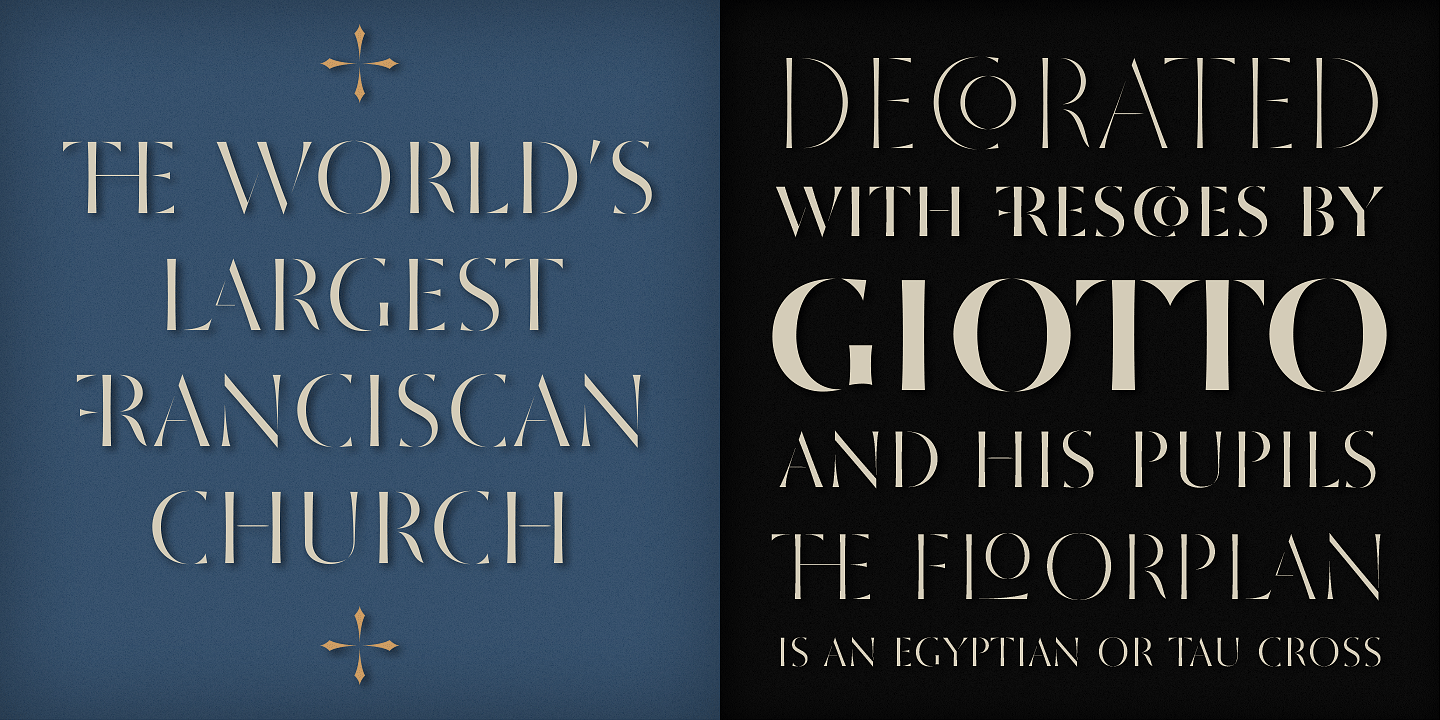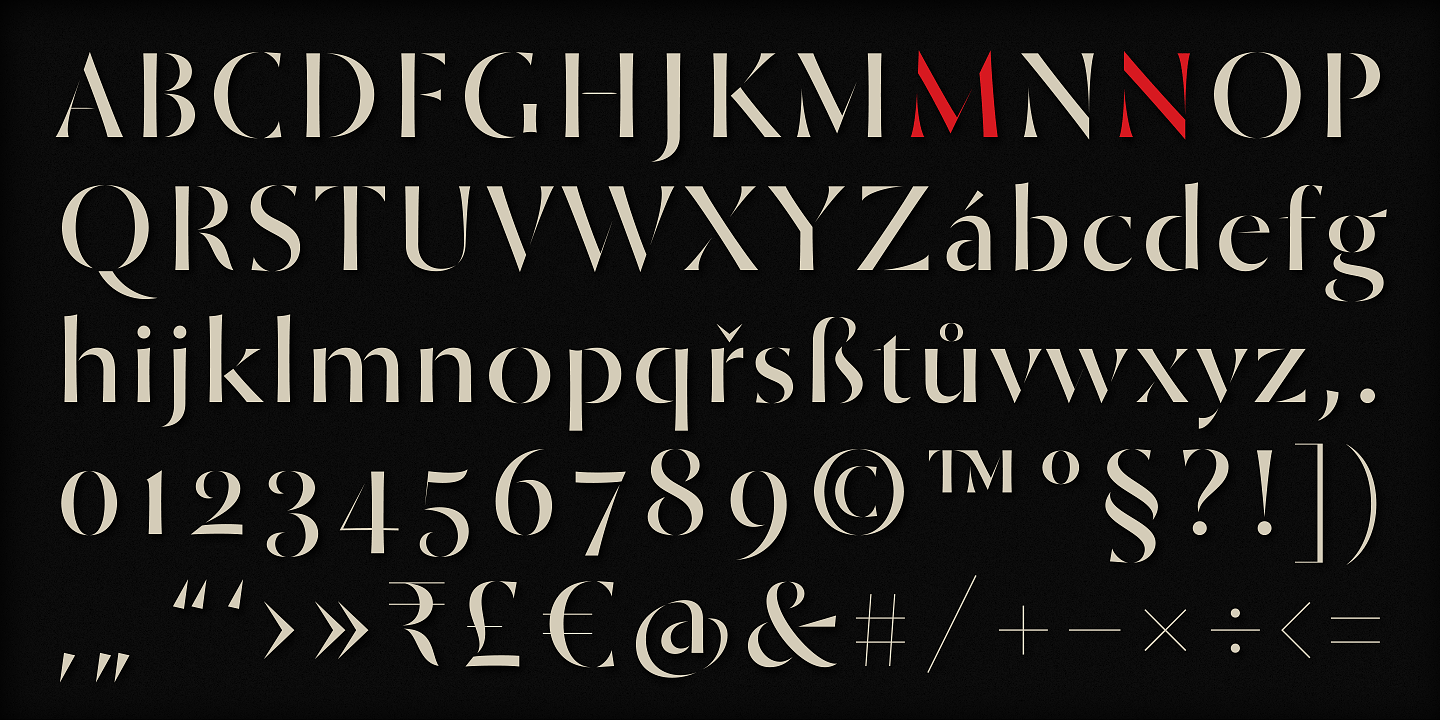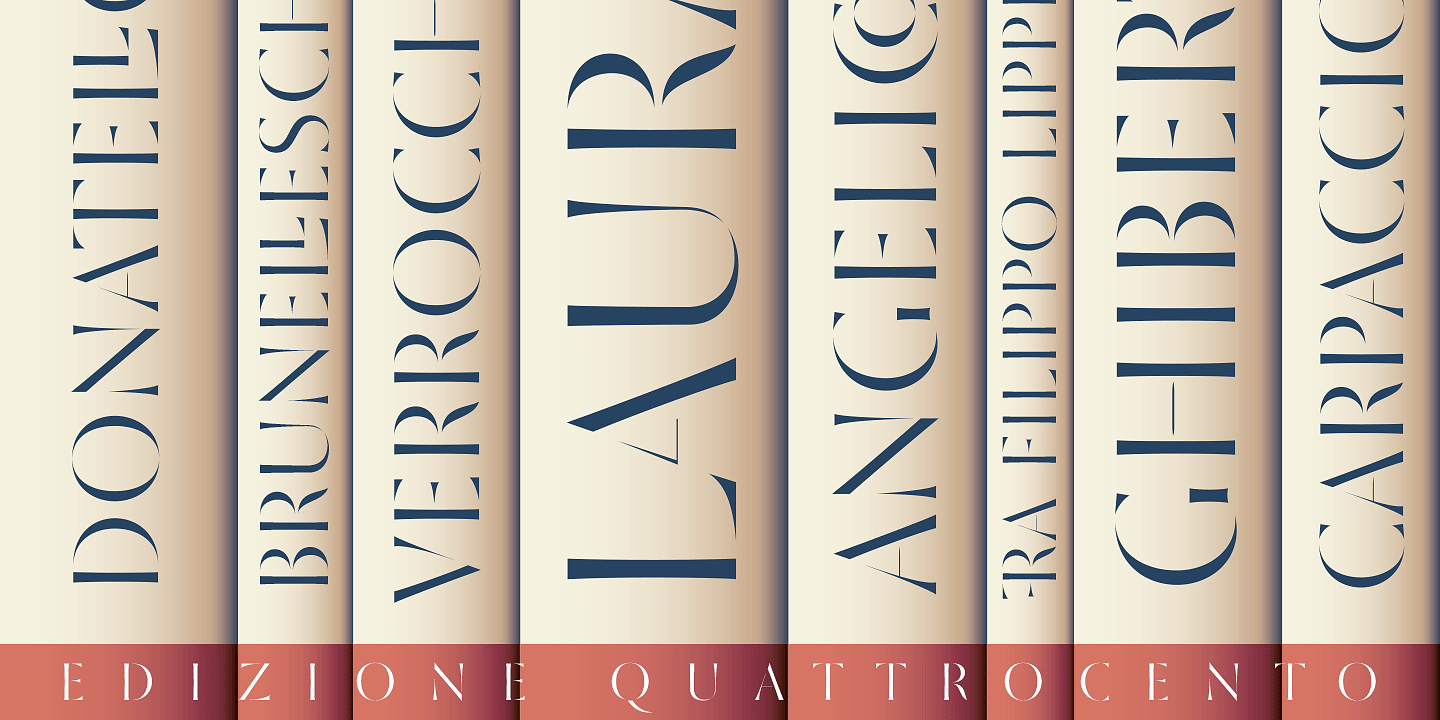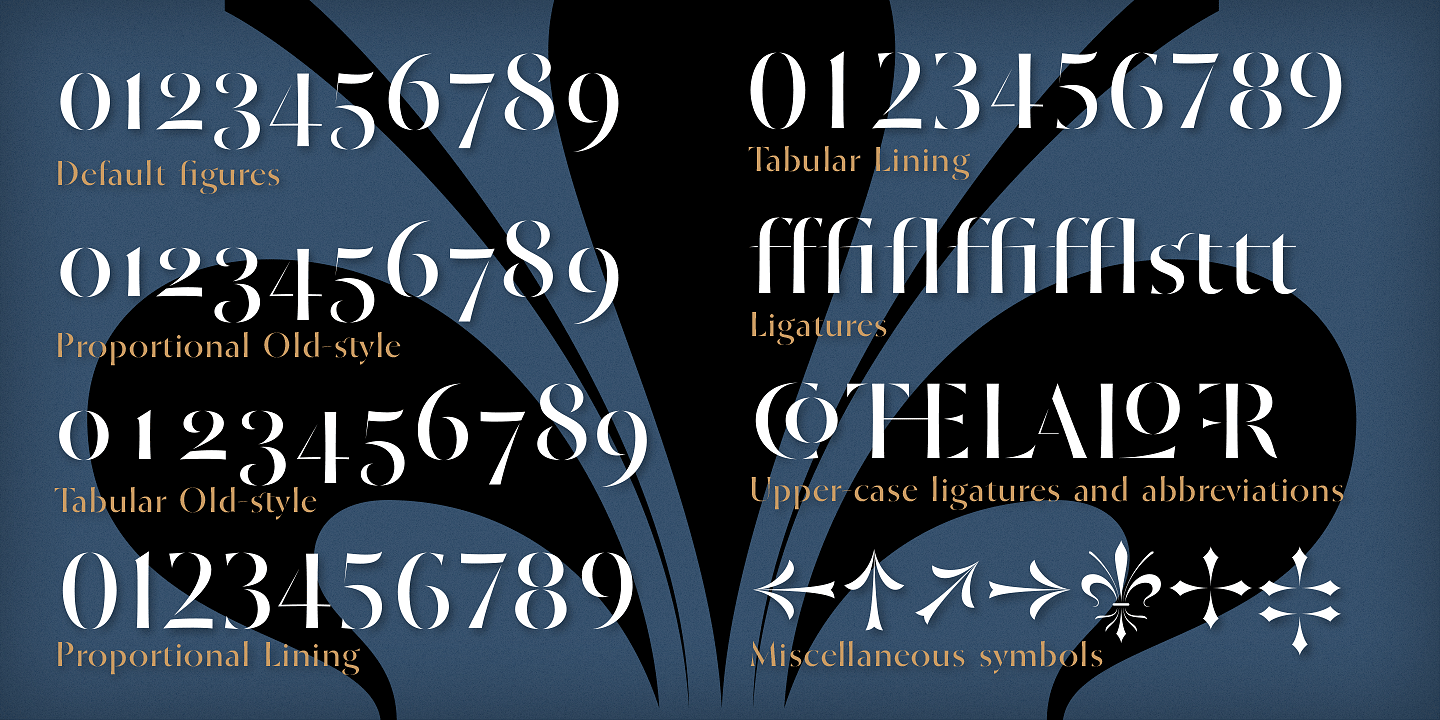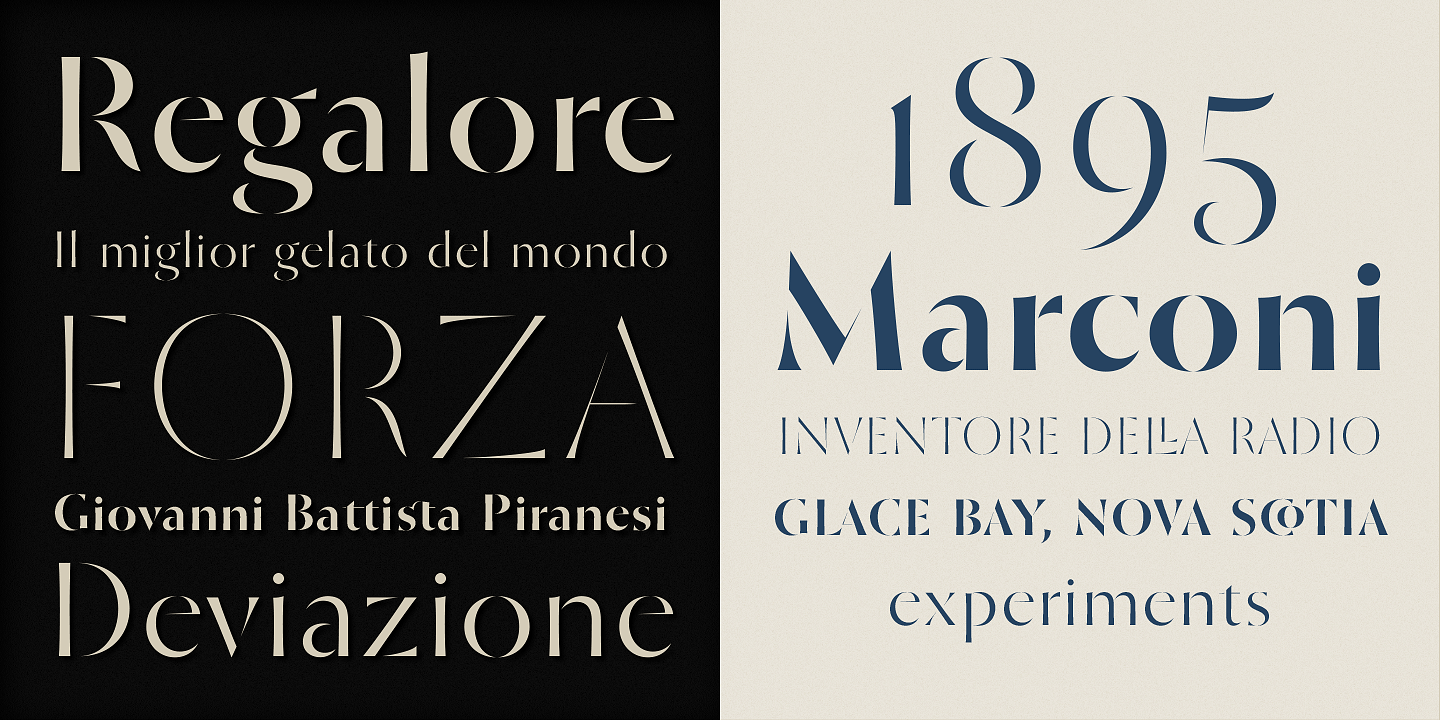
Die Geburtsstätte der St Croce befindet sich auf den Grabsteinen der Basilika Santa Croce in Florenz. Anstatt die Abnutzung, die die Schriftzüge in den vergangenen Jahrhunderten erlangt haben bei der Digitalisierung rückgängig zu machen, dokumentiert das Design der St Croce den Verfall. Hermann Zapf’s Optima dagegen wurde von denselben Grabsteinen inspiriert, führte jedoch zu einem ganz anderen Ergebnis.
Die Schrift ist aufgrund ihrer filigranen Erscheinung eher für Schaugrößen-Anwendungen wie Kataloge, Buchumschläge, Einladungen und Plakate geeignet.